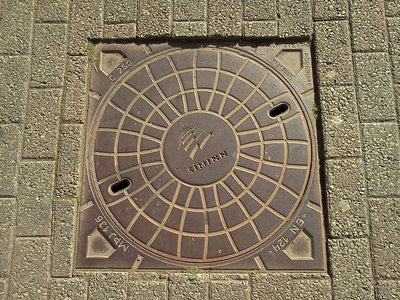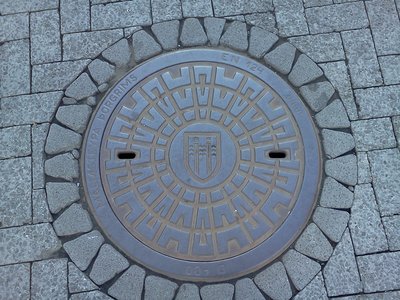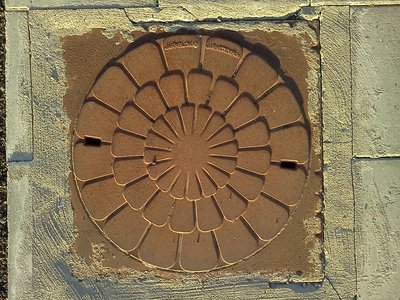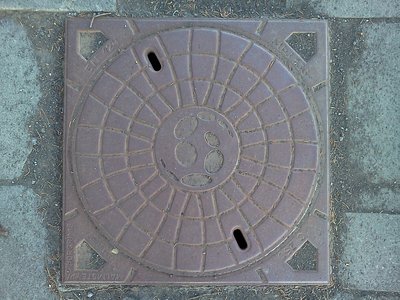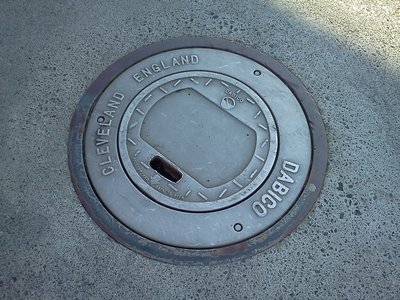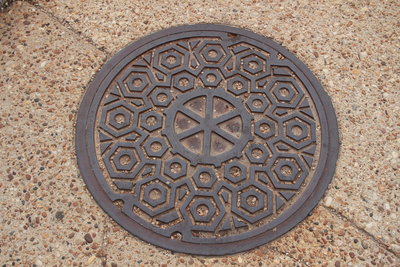
Aber wie groß ist da die Zielgruppe? Lohnt sich das? Kann Freund Pachulke mit so einem Buch reich werden? Na ja, zumindest der Druck sollte ja kein Problem sein … Ich biete Unterstützung beim Layout an. Oder beim Bücher binden – falls Pachulke mich anlernt …
Es wäre genug da für eine mehrbändige Serie.
Es gab (über ein Buch) schon mal ein Vorgespräch mit dem Hermann-Schmidt-Verlag. Die hättens auf mein Risiko verlegt, also wenn ich die Auflage vorfinanziert hätte. So nötig habe ich die Publikation nun aber auch nicht. Es gibt übrigens auch schon schöne Bücher zum Thema.
das muss man ja gar nicht so groß aufziehen. ein kleines buch mit einem 'best of german gullideckels' im selbstverlag reicht doch auch. eventuell wil das ja sogar ein hersteller dieser deckel finanzieren, hmm... jetzt wo ich drüber nachdenke: hast du deine fotos schonmal einem hersteller angeboten, für einen kalender oder etwas ähnliches?
Dier Herstellung wäre sicher lösbar, aber wie willst Du das mit dem Vertrieb machen? Und die Gießer haben naturgemäß wenig Interesse an der Darstellung schöner Deckel von anderen Gießereien.
Und noch ein paar Einzelexemplare, die mir in den letzten Jahren vor die Linse gekommen sind.
Aus Reykjavík:
Selfoss (auch in Island):
und zu guter Letzt noch eins von zwei identischen Exemplaren vor dem Smithsonian Institution Building in Washington:
Ah, ein Dresdner in Wolgast. Bei dem hats mit dem Aussterben aber noch ein bißchen Zeit, da liegen gefühlte Hunderttausende im ganzen Ostblock.
Es sind eben weniger die Deckel, die den Anlass zum Verschwinden geben, sondern viel mehr, der Beton darunter, der mittlerweile marode ist (Dank RGW-Magerbeton, denn aus den Betrieben war immer noch ein wenig mehr herauszuholen, und so verschwand wohl im Betonwerk so mancher volkseigener Betonsack auf dem Weg zum volkseigenen Häuslebau, den Kanal-Betonringen sah man die etwas gestreckte Misching ja nicht gleich an, und gehalten haben sie ja, bis jetzt...), und kommen neue Betonringe, bringen die eben auch ihr neues Deckelchen mit.
Beim Betrachten ist mir zum ersten mal aufgefallen, wie schön und voller Symbolik diese Deckel sind.
Die Randgestaltung mit Wappen und Mauerkronen :-? scheint mir jedenfalls ein subtiles Bekenntnis zu städtisch-bürgerlich-republikanischem Selbstbewusstsein zu sein. Und gelöst wurde das, sowohl durch die Einbeziehung an die funktionalen Antirutschbipusse im Inneren als auch die symmetrische Gestaltung m.E. erheblich besser als beim neuen kommunalen Standardmodell, bei dem einfach das Stadtwappen möglichst groß auf einem 0850-Deckel zentriert wird. Bei letzterem sieht der Passant das Stadtwappen dann ja auch in 90% der Fälle das Wappen schief oder auf dem Kopf. Lokalpatriotismus will sich da bei mir nicht einstellen.
…Vielleicht liegt es ja daran, dass die US-Deckel außer Hardcorefans wirklich kaum jemandem fotografierwürdig erscheinen.
Terroristen. Wenn ich daran denke, dass beim G7-Gipfel im Umkreis von vielen Kilometern alle zugeschweißt wurden, würde ich in USA keine fotografieren. Die Erklärung, dass es wirklich nur der Deckel ist, der interessant ist, wird mir die CIA nicht glauben …
Re Norwegen, Zelle, Auto zerlegt:  :shock:  :trost:
Beim Betrachten ist mir zum ersten mal aufgefallen, wie schön und voller Symbolik diese Deckel sind.
Sie sind wirklich auf eine schlichte Art perfekt.
Die Erklärung, dass es wirklich nur der Deckel ist, der interessant ist, wird mir die CIA nicht glauben …
Dass ich durch Skandinavien fuhr, um Verkehrsschilder zu fotografieren, wollten mir die norwegischen Grenzer vor ein paar Jahren auch nicht glauben  …
Gut, wenn man in solchen Fällen auf eine umfangreiche Sammlung von Kanaldeckeln oder Verkehrsschildern im Netz verweisen kann, um sich zu legitimieren. Vielleicht erscheint es ja doch plausibel, daß niemand über Jahre hinweg solche Photos macht, nur um irgendwelche finsteren Praktiken zu vertuschen.
drum hab ich eben auch mal so einen Massenware-Normalo gezeigt. Jeder, der so etwas knipst, fotografiert die besonderen, und die ganz normalen, die zu Millionen herum lagen verschwinden so langsam sang und klanglos, und plötzlich sind sie weg.
Und betrachte ich die Fotos, die meine Eltern gemacht haben, zeigen sie einen klitzekleinen Peter, einen größeren Peter... Aber nie die ganz normale Umgebung, an die sich der große Peter heute gern wieder erinnern würde. Die Dinge, die in der jeweiligen Zeit ganz normal waren.